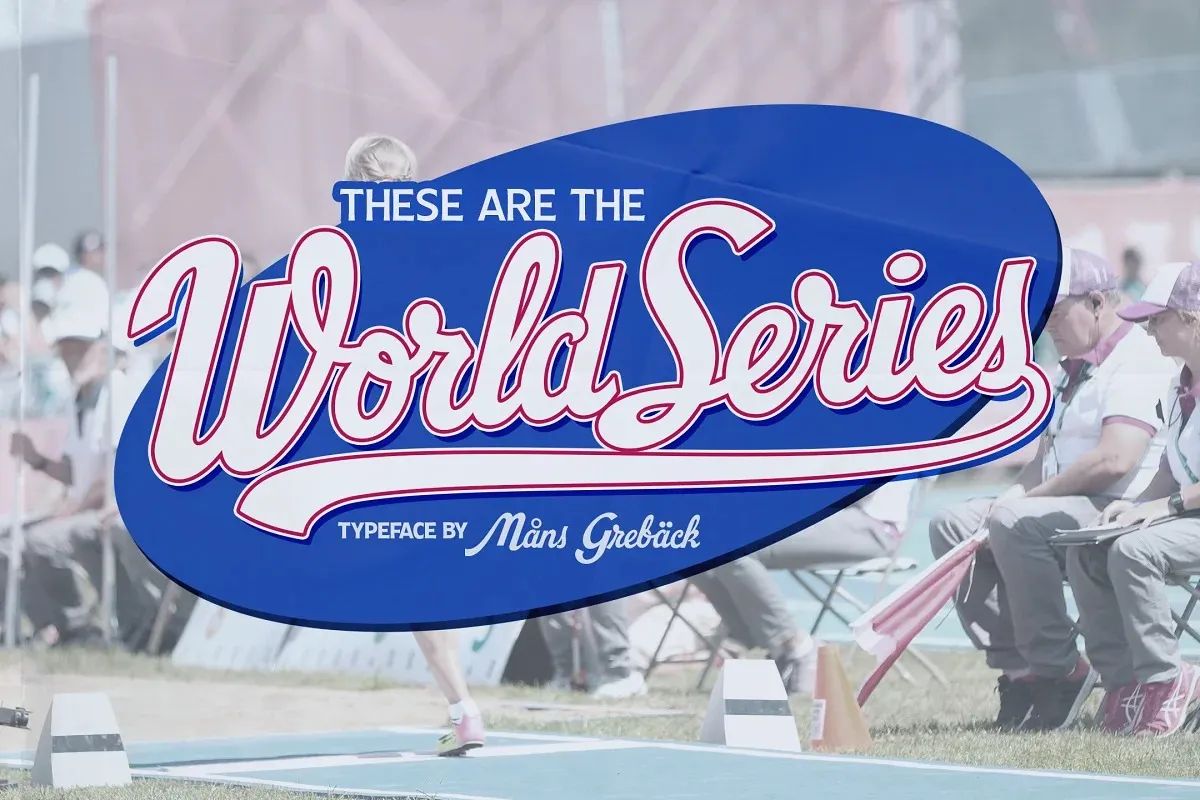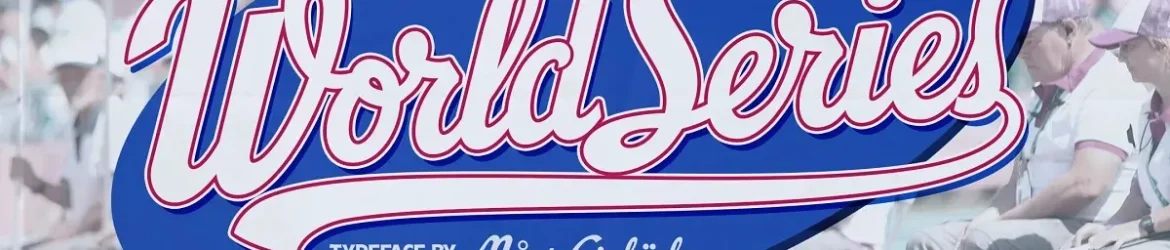
World Series Script Font – Download Grátis
Esta fonte é inspirada no estilo retro e combinado com a letra à mão. Tem muitas alternativas de salsichos e ligaduras para personagens que permitem uma gama ampla de personalização, permitindo que você monte sua própria composição criativa. Através da abrangente versatilidade das feições serifadas, este estilo tem um aspecto de letra à mão confiante, com uma aparência vintage perfeitamente adequada tanto para uso em logotipos quanto para qualquer arte tipográfica que precise parecer personalizada. Desenhada e criada por Mans Greback em 2021, a World Series Script Font oferece opções de estilização alternativa, conjunto estilístico, ligaduras e salsichos, permitindo-lhe explorar diferentes formatos do texto para atender aos seus requisitos específicos.